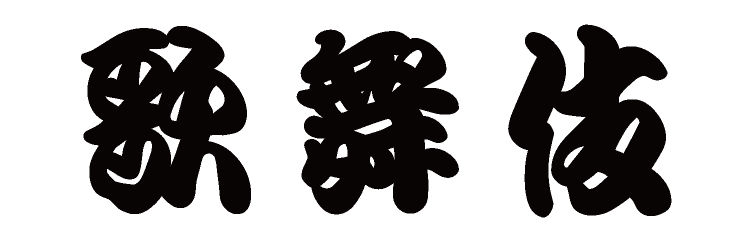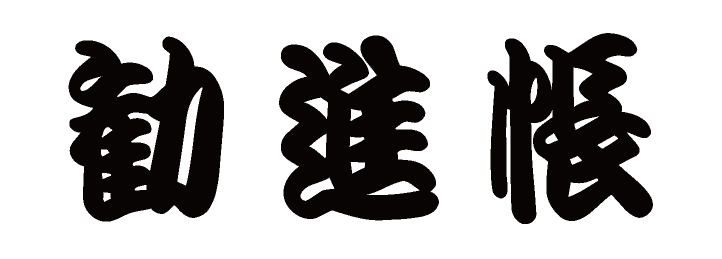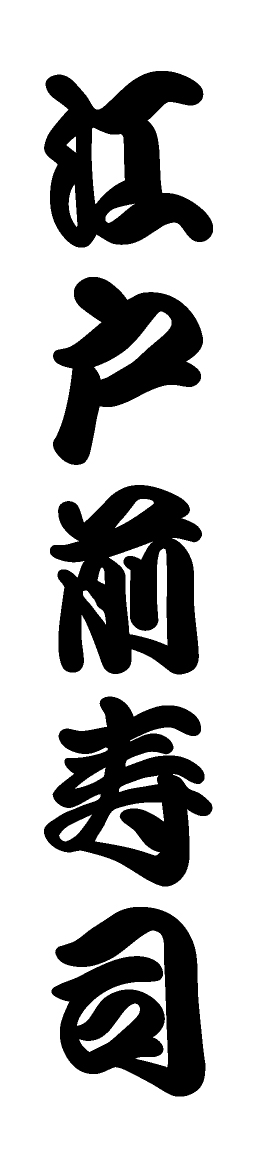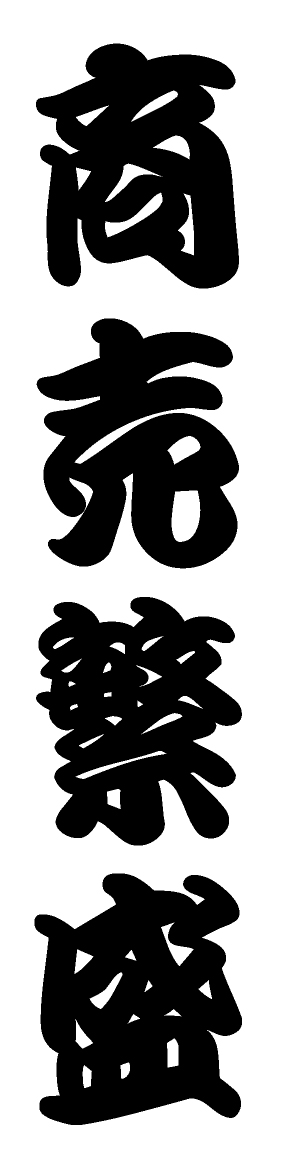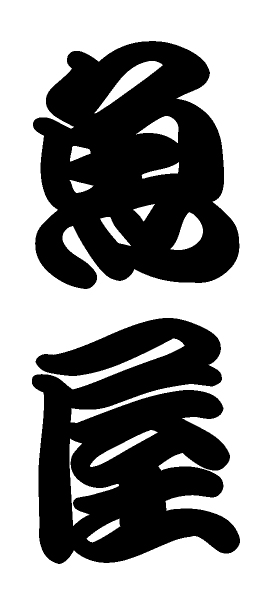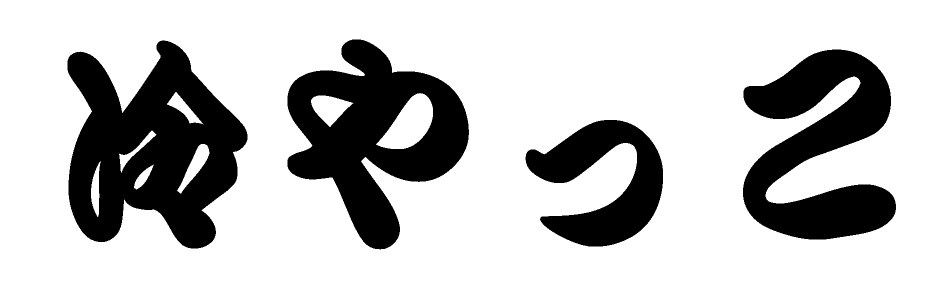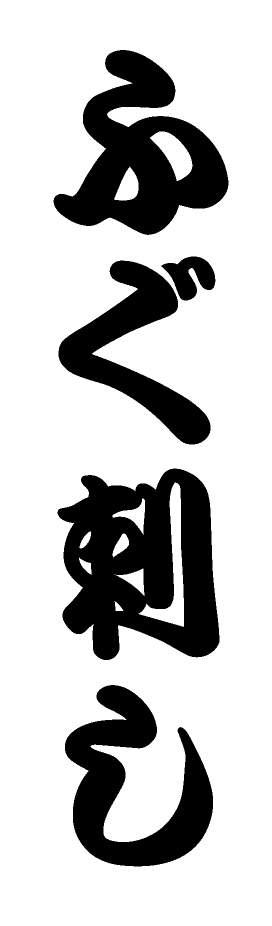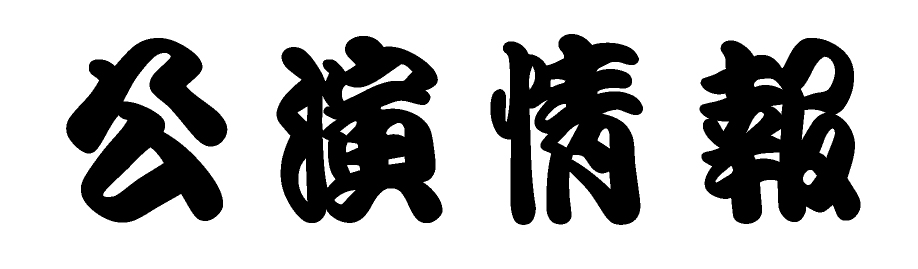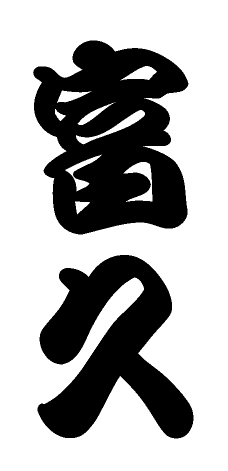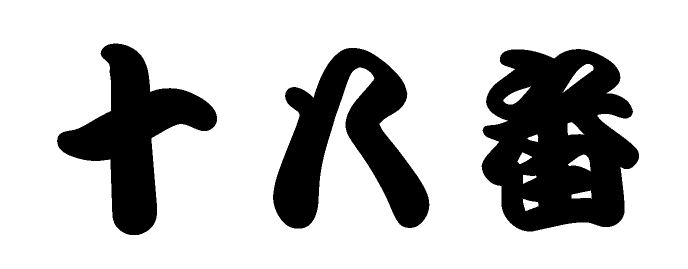
かんてい流マール (ダウンロード版)
【書:原田正春】
弊社書籍『ディスプレイ書体集 新かんてい流』(原田正春 著)をフォント化したものです。江戸の歌舞伎から生まれた勘亭流文字。本素材は、勘亭流の伝統をふまえながら、現代の人々が読みやすいように書体に工夫を加えています。看板や広告に広く愛用されている風格のある書体で、特徴的なデザインは遠くからでも人目を引きつけます。フォントフォーマットはTrueTypeです。印刷物への使用など一般的な商業利用は追加料金なしで可能です。詳細については、上記リンク「使用許諾範囲」を、ご購入前に必ずご確認ください。